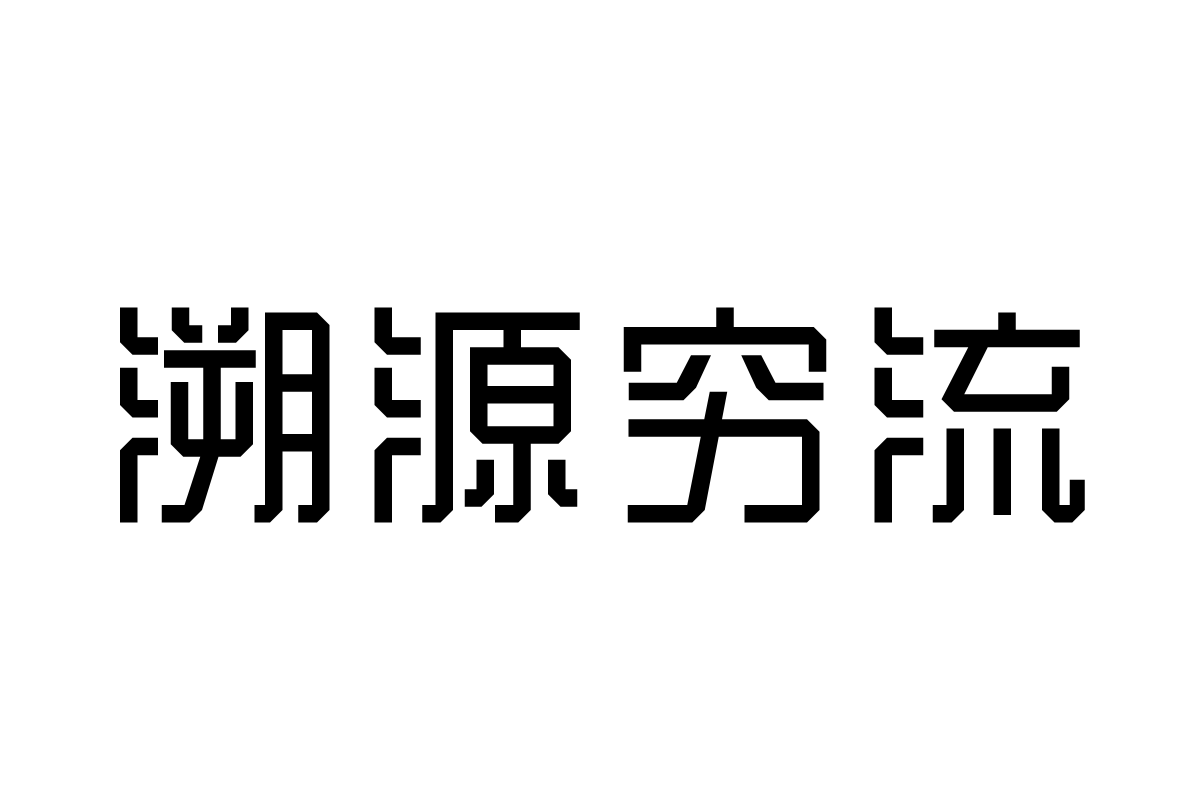
三极惊蛰简体字体是专为汉字书写设计的字体,具有以下特点:
1. 字形简洁:三极惊蛰简体字体的字形设计简洁明了,易于阅读和书写。
2. 笔画流畅:该字体的笔画流畅自然,符合汉字书写的规律和习惯。
3. 结构合理:三极惊蛰简体字体的结构合理,各个部分之间的比例协调,整体美观大方。
4. 风格独特:该字体具有独特的风格,既保留了传统的韵味,又融入了现代的设计元素,给人以新颖的感觉。
5. 适用性强:三极惊蛰简体字体适用于各种场合,如书法、印刷、电子屏幕等,具有较强的适用性。
总之,三极惊蛰简体字体是一款适合现代汉字书写的字体,具有简洁、流畅、结构合理等特点,能够满足不同场景下的书写需求。